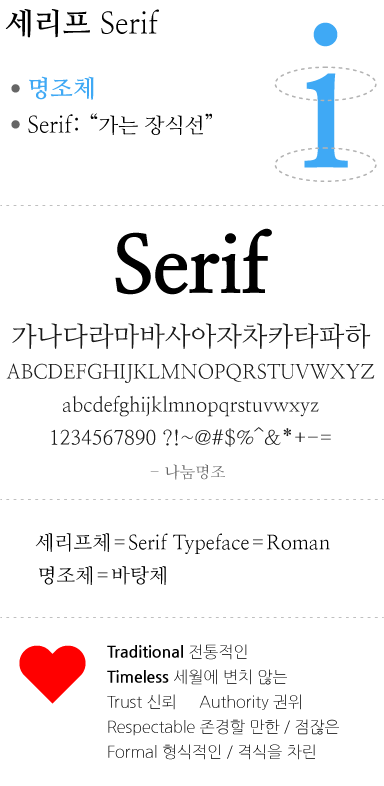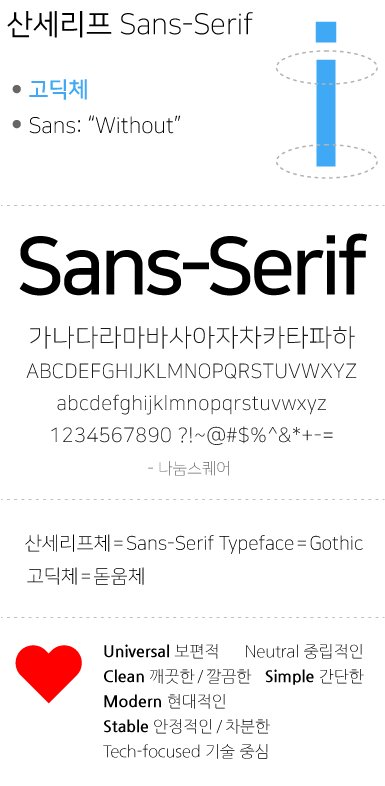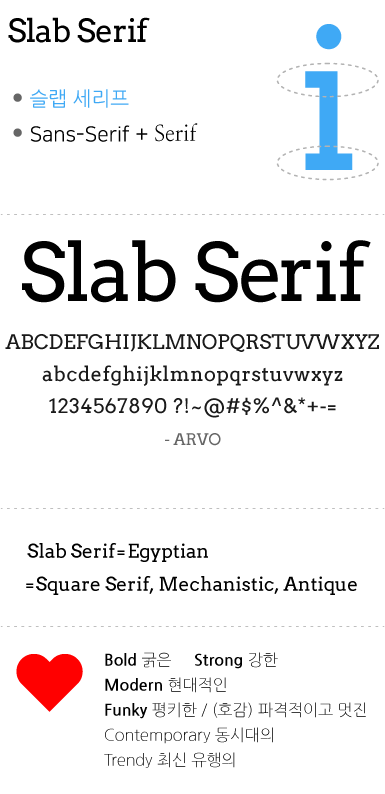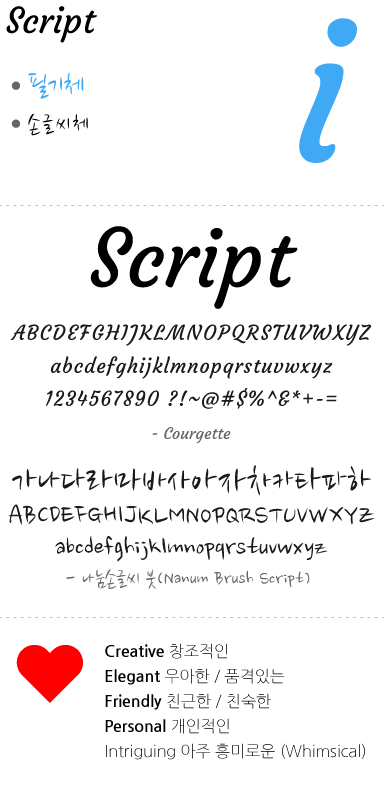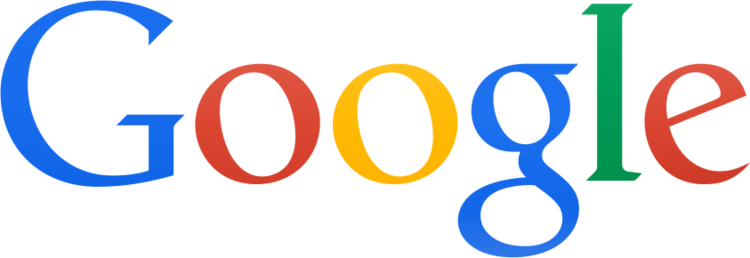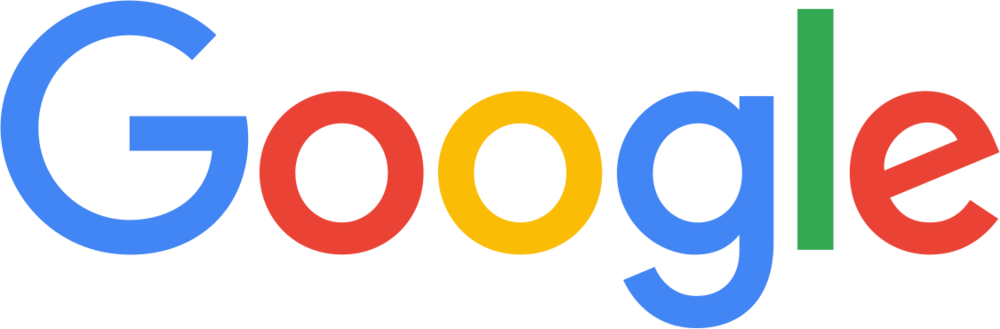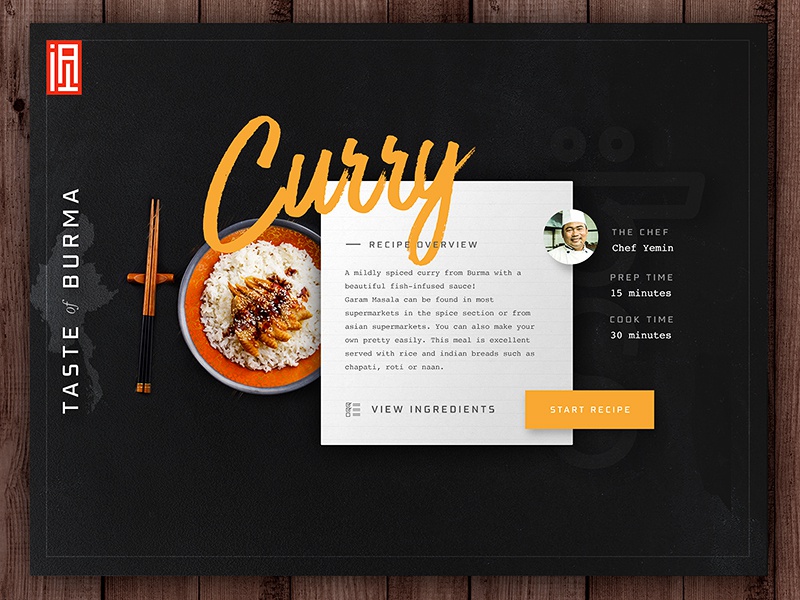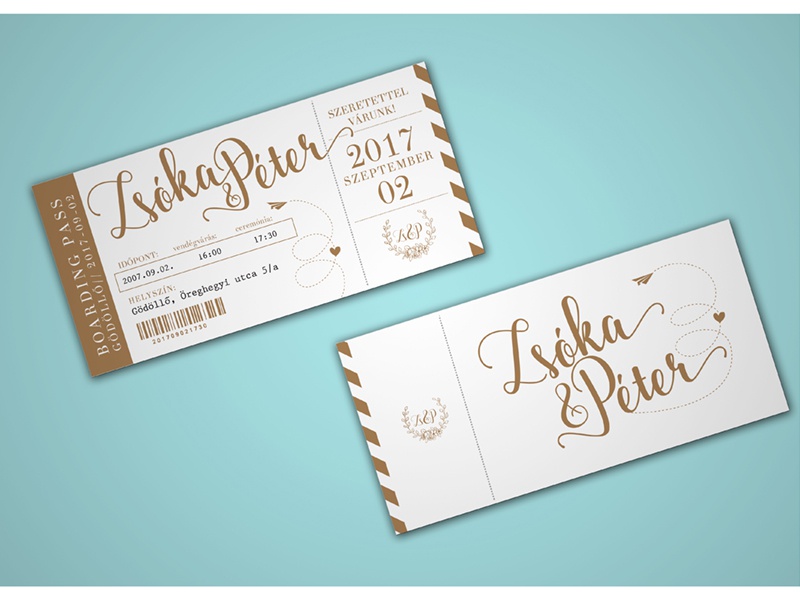
[Design] 어떤 폰트를 사용할 것인가? 폰트의 종류와 의미
이전에 디자인에 적용할 수 있는 색의 의미와 형태의 의미에 대해서 알아보았습니다. 그렇다면 이번에는 폰트가 인간에게 심리적으로 전달하는 감성의 의미가 어떻게 되는지 폰트의 종류별로 조사해보도록 하겠습니다.
폰트의 종류와 의미
폰트의 종류로 대표적인 Serif(세리프), Sans-Serif(산세리프), Slab Serif(슬랩 세리프), Script(스크립트)를 통해 폰트의 의미와 적용된 디자인 사례에 대해 알아보도록 하겠습니다.
기획의 주제에 맞는 디자인을 하는데 중요한 것이 색의 의미, 형태의 의미, 폰트의 의미를 파악하고 활용하는 것입니다. 또한, 기획의 주제에 맞는 디자인 자료를 찾는 데도 이러한 디자인 구성 요소의 의미를 통해 분석하는 능력이 필요합니다.
1. 폰트의 종류와 의미
1) 세리프(Serif)
① About Serif
세리프(Serif) 폰트는 영문 폰트로는 로만체(Roman), 한글 폰트로는 명조체, 바탕체를 얘기합니다. 책과 같은 인쇄물에 많이 사용하는 글꼴입니다.
‘Serif‘의 뜻은 ‘가는 장식선‘이라고 합니다. 활자(Type)에서 획의 시작이나 끝부분에 돌출되어 있는 부분을 지칭합니다. 장식처럼 돌출되어 있는 세리프 부분이 산세리프(Sans-Serif) 폰트와 구분하는 특징입니다.
② 세리프(Serif) 폰트
• 세리프 영어 폰트: Times New Roman, Georgia, Garamond, Baskerville
• 세리프 한글 폰트: 신명조, 바탕체, 한초롬바탕, 나눔명조, 본명조(Noto Serif KR, Source Han Serif Korean)
③ 세리프(Serif) 폰트의 의미
세리프체는 전통적인, 세월이 흘러도 변치 않는(Timeless) 의미가 대표적이며 그래서 신뢰, 존경, 권위의 느낌을 줍니다.
• Traditional 전통적인
• Timeless 세월에 변치 않는
• Trust 신뢰
• Reliable 신뢰할 수 있는
• Respectable 존경할 만한
• Authority 권위
• Formal 형식적인
• Sophisticated 세련된
• Comfort 편안함
• Practical 경험이 풍부한
• Impressive 인상적인
④ 세리프(Serif) 폰트가 적용된 로고 디자인
오래된 전통 있는 고급 브랜드의 로고타이프(Logotype)에 많이 사용됩니다.
2) 산세리프(Sans-Serif)
① About Sans-Serif
산세리프(Sans-Serif) 폰트로는 고딕체(Gothic)와 돋움체가 있습니다. 현대 디지털 기기에 가장 많이 사용하고 있는 폰트입니다.
‘Sans-Serif’에서 ‘Sans‘는 프랑스어로 ‘Without, …없는‘을 뜻합니다. 그래서 ‘Sans-Serif’는 ‘Without Serif’, 즉 ‘가는 장식선이 없는’을 의미합니다. 세리프체가 정교하다면, 산세리프체는 심플합니다.
장식이 없는 심플한 산세리프체는 인간에게 폰트에서 인지할 정보(장식, Serif)가 적기 때문에 읽기 쉬운 글꼴입니다.
디지털 환경에서 세리프(Serif) 폰트
디지털 환경에서 산세리프(Sans-Serif) 폰트
컴퓨터와 핸드폰이 보급되면서 디지털 환경에 친화적인 산세리프체, 고딕체가 많이 사용되고 있습니다. 그래서 일반적으로 사용자에게 산세리프체, 고딕체가 익숙한(Familiar) 폰트가 되었습니다.
하지만 현재 디지털 기술의 발전으로 인하여 고밀도/고해상도 디스플레이가 보급되면서 앞으로는 세리프체, 명조체 또한 많이 사용될 것으로 예상합니다.
② 산세리프(Sans-Serif) 폰트
• 산세리프 영어 폰트: Helvetica, Verdana, Arial, Century Gothic, Myriad, Calibri, Roboto
• 산세리프 한글 폰트: 굴림체, 한초롬돋움, 나눔고딕, 나눔스퀘어, 본고딕(Noto Sans KR, Source Han Sans Korean)
③ 산세리프(Sans-Serif) 폰트의 의미
산세리프체는 심플하고 간단한 기하학적인 형태의 글꼴로 깨끗하고 현대적인 의미를 지닙니다. 보편적이고 안정적이며 중립적인 느낌을 표현 할 수 있습니다.
• Universal 보편적인
• Clean 깨끗한 / 깔끔한
• Modern 현대적인
• Stable 안정적인 / 차분한
• Simple 간단한
• Straightforward 간단한
• Geometric 기하학적인
• Neutral 중립적인
• Objective 객관적인
• Tech-focused 기술 중심
• Cutting-Edge 최첨단의
• Sensible 분별 있는
• Easy to Read 읽기 쉬운
④ 산세리프(Sans-Serif) 폰트가 적용된 로고 디자인
기술 중심의 최첨단 적인 의미로 IT 업체나 벤처 기업에서 많이 사용되는 폰트이기도 합니다. 로고 디자인에 있어서 사각형(Square, Rectangle)과 함께 가장 많이 사용되고 있는 폰트가 산세리프체입니다.
3) 슬랩 세리프(Slab Serif)
① About Slab Serif
슬랩 세리프(Slab Serif)체는 산세리프를 중심으로 세리프의 장식을 융합한 서체라고 생각하면 이해가 쉬울듯 합니다. 강하고 볼드한 글꼴로 제목에 주로 사용되며, 트렌디한 느낌을 반영할 수 있습니다.
슬랩 세리프는 ‘이집션(Egyptian)’, ‘Square Serif’, ‘Mechanic’, ‘Antique’로도 불립니다. 1차 산업혁명 시대에 로버트 손(Robert Thorn)이 슬랩 세리프 활자를 개발하고 명명한 ‘이집션(Egyptian)’은 이집트의 건축 양식에서 영향을 받았다고 합니다.
슬랩 세리프체는 제목에 사용하면 강하고 현대적이고 멋진 스타일을 표현할 수 있습니다. 페스티벌과 콘서트와 같은 이벤트에 활용하기 좋은 스타일입니다.
하지만 대부분 볼드체에 속하기 때문에 본문에 사용하면 가독성이 저하되는 서체입니다!
② 슬랩 세리프(Slab Serif) 폰트
• 슬랩 세리프 영어 폰트: Rockwell, Courier, Museo, Clarendon, Bevan
• 슬랩 세리프 한글 폰트: 산돌구름에서 제작한 ‘곧은부리‘
③ 슬랩 세리프(Slab Serif) 폰트의 의미
• Bold 굵은
• Strong 강한
• Solid 단단한
• Modern 현대적인
• Contemporary 동시대의
• Trendy 최신 유행의
• Funky 펑키한
• Friendly 친한
• Confirmed 확고부동한
④ 슬랩 세리프(Slab Serif) 폰트가 적용된 로고 디자인
⑤ 슬랩 세리프(Slab Serif) 폰트가 적용된 영화 포스터 디자인
출처: IMDB
출처: Wikipedia
출처: IMDB
4) 스크립트(Script)
① About Script
스크립트(Script) 폰트는 필기체, 손글씨체입니다. 친근하고 크리에이티브한 스타일이지만, 중요한 것은 읽기 쉬운지 가독성에 신경을 써야 하는 글꼴입니다.
스크립트체는 손으로 쓴 느낌의 서체이기 때문에 친숙하고, 다른 폰트의 종류와 차별화되는 형태로 창조적이고 흥미로운 느낌을 줍니다.
하지만 잊지 마세요! 스크립트체, 필기체는 본문에 사용하면 가독성이 저하되는 서체입니다!
(참조: 글의 가독성을 높이는 방법 1: 본문에 사용하면 안 되는 폰트 스타일과 속성)
② 스크립트(Script) 폰트
③ 스크립트(Script) 폰트의 의미
스크립트 영어 폰트의 경우, 스타일에 따라 우아하고 세련되고 장식적인 느낌과 고전적인 의미를 부여할 수 있습니다. 스크립트 한글 폰트의 경우, 손글씨의 느낌이 강한 서체가 많으며 그래서 친숙하고 개인적이며 흥미로운 감성을 전달할 수 있습니다.
• Creative 창조적인
• Friendly 친숙한
• Personal 개인적인
• Happy 행복한
• Elegant 우아한
• Sophisticated 세련된
• Stylish 멋진
• Fancy 장식적인
• Classic 고전적인
• Formal 형식적인
• Intriguing 아주 흥미로운
• Whimsical 기발한
④ 스크립트(Script) 폰트가 적용된 로고 디자인
스크립트체, 필기체가 적용되면 회사의 브랜드를 고객에게 개인적인 느낌을 줄 수 있어 선호도를 높일 수 있습니다. 음식이나 음료 브랜드에 자주 적용되는 폰트입니다.
⑤ 스크립트(Script) 폰트가 적용된 디자인
웹 디자인
출처: Nathan Riley
결혼식 초대장 디자인
출처: enno
스크립트 폰트를 디자인에 적절히 사용하면 크리에이티브한 느낌을 살릴 수 있습니다. 그리고 웨딩 관련 디자인에 자주 사용되는 이유 중 스크립트체, 필기체가 가지는 우아하고 세련된 스타일을 전달할 수 있기 때문입니다.
기획의 주제에 맞는 색의 의미, 형태의 의미, 폰트의 의미를 고려하여 적용하면 일관성 있는 좋은 디자인을 할 수 있습니다! 그리고 이러한 디자인 구성 요소의 의미를 통해 디자인을 분석할 수 있다면 내가 필요한 기획의 컨셉에 맞는 좋은 디자인 자료들을 선택할 수 있을 것입니다!
2013 – 2015
2015 – 현재
새로운 로고 디자인의 변화에 대한 구글 측의 발표에서도 알 수 있듯이 가장 큰 이유는 스마트폰의 보급에 따른 새로운 디지털 미디어 환경의 변화에 대한 적응이 가장 중요한 니즈(Needs)였다고 생각합니다.
첫째, 산세리프 폰트, 고딕체는 형태의 특성상 디지털 환경에서 세리프 그리고 다른 스타일의 폰트보다 높은 가독성을 구현하는 글꼴입니다.
둘째, 산세리프 폰트를 통해 사용자가 심리적으로 느끼는 감성에는 현대적이고 최첨단 기술 중심적인 의미가 있습니다. 실제로 당시 실리콘 밸리로 대표되는 유망한 IT 업체와 벤처 기업의 로고를 보면 전반적으로 산세리프 스타일로 디자인되었습니다.
이처럼 폰트의 의미를 파악하고 있으면 디자인을 분석하는데 용이합니다.
해당 디자인에 폰트가 적합하게 적용되어 디자인되었는지 분석할 수 있는 능력을 키우면 좋은 디자인을 고르고 선택할 수 있을 것입니다.
또한, 이러한 디자인 분석 능력이 좋은 디자인을 할 수 있는 한 방법입니다!